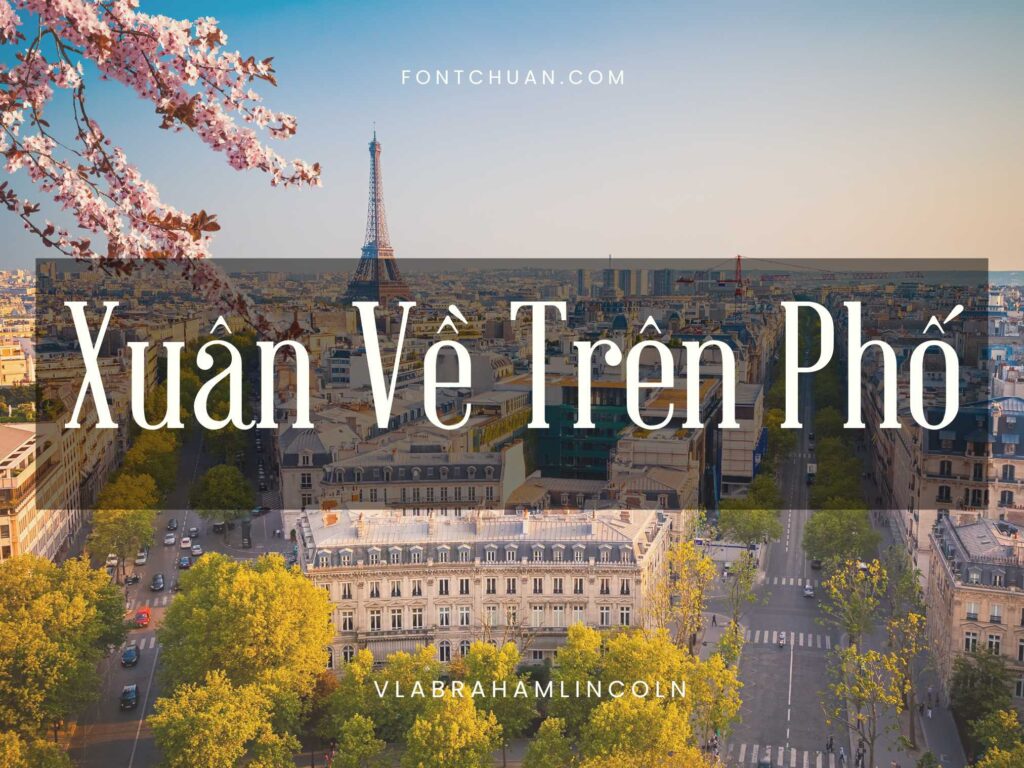
Font VL Abraham Lincoln Việt Hóa
VL- Abraham-Lincoln là một phông chữ serif được thiết kế bởi Frances MacLeod. Phông chữ này lấy cảm hứng từ tỷ lệ của vị Tổng thống thứ 16 của Hoa Kỳ và các quảng cáo, áp phích từ thế kỷ 19. Với sự tương phản vừa phải và chân chữ vững chắc, VL- Abraham-Lincoln mang lại cảm giác cổ điển và trang nhã.
VL- Abraham-Lincoln đã được Việt hóa bởi **Việt Linh**, hỗ trợ đầy đủ các ký tự tiếng Việt, giúp người dùng dễ dàng sử dụng trong các dự án sáng tạo. Phông chữ này được thành viên **Font Chuẩn** lựa chọn, sưu tầm và giới thiệu nhằm phục vụ nhu cầu thiết kế đa dạng.
Với thiết kế thanh lịch và rõ ràng, VL- Abraham-Lincoln phù hợp cho các ứng dụng như tiêu đề, văn bản dài, thiết kế logo và các ấn phẩm in ấn. Trong lĩnh vực sự kiện, phông chữ này có thể được sử dụng trong các dịp như hội nghị, lễ kỷ niệm và các sự kiện văn hóa. Ngoài ra, VL- Abraham-Lincoln cũng thích hợp cho các ngành nghề như xuất bản, giáo dục và truyền thông.